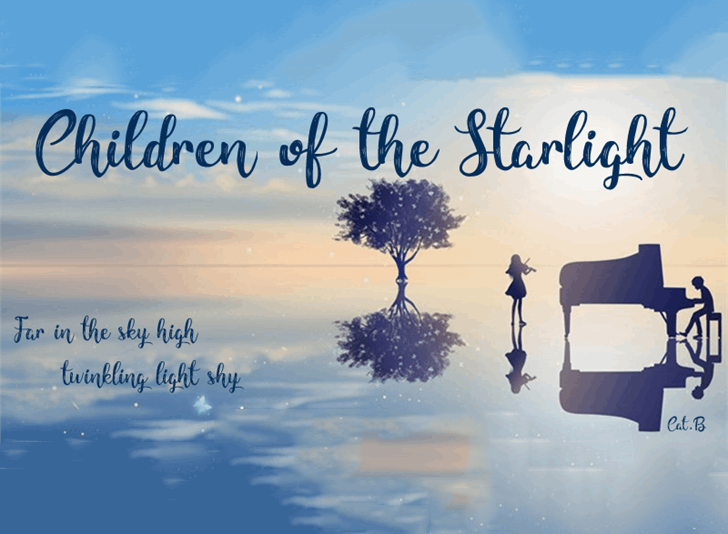
Children of the Starlight Font – Download Grátis
Descubra a Children of the Starlight Font, uma elegante e sofisticada família de tipografia que traz uma vibe fluida e versátil perfeita para projetos pessoais e até mesmo alguns elementos comerciais, mas requer um pouco de atenção ao usar em conteúdos sexuais. O designer Cat Butcher criou esta fonte com arte inspiradora e originalmente permitiu seu uso gratuito por meio de uso personalizado. Cat Butcher é conhecido como um dos principais nomes no mundo da tipografia, proporcionando uma variedade de fontes elegantes que vão desde elegância até um toque mais casual. Se você está procurando uma fonte com estilo único para seus projetos, pode considerar a Children of the Starlight Font, especialmente se sua ideia envolver algo relacionado à estrelas ou é lúdico e criativo. Para acessar a versão completa da fonte e garantir seu uso, lembre-se de entrar em contato com Cat Butcher por meio do email:  Seja o próximo artista que ele seleciona para sua família de fontes, contribuindo ainda mais para esta biblioteca valiosa de recursos gráficos.